45+ font chữ 8/3 Việt hóa đẹp, miễn phí và hot trend 2026
Chọn ngay bộ sưu tập 45+ font chữ đẹp để tạo nên những tấm thiệp quà tặng 8/3 ý nghĩa. Lựa chọn font chữ phù hợp giúp thông điệp chúc mừng càng thêm tinh tế và ấn tượng!
Trong thiết kế đồ họa, font chữ không chỉ là phương tiện truyền tải thông tin mà còn là linh hồn thể hiện phong cách của tác phẩm. Với chủ đề tôn vinh phái nữ, các font chữ cần sự mềm mại, uyển chuyển hoặc sang trọng đặc trưng. Bài viết này mình sẽ tổng hợp những bộ font chữ 8/3 được ưa chuộng nhất.
Top font chữ 8/3 đẹp và phổ biến nhất hiện nay
Những font chữ dưới đây dẫn đầu xu hướng năm 2026 nhờ tính thẩm mỹ cao và sự linh hoạt trong sử dụng:
Apricots – Nét viết tay nhẹ nhàng, thanh lịch
Apricots mang đến cảm giác gần gũi như nét chữ viết tay thật. Đây là lựa chọn lý tưởng cho các mẫu thiệp chúc mừng mang phong cách tối giản nhưng vẫn giữ được sự tinh tế.
Great Vibes – Sự uyển chuyển, bay bổng cho lời chúc
Với những đường lượn sóng điệu đà, Great Vibes cực kỳ phù hợp cho các câu slogan như "Happy Women's Day" nhờ độ bay bổng và đầy nữ tính.
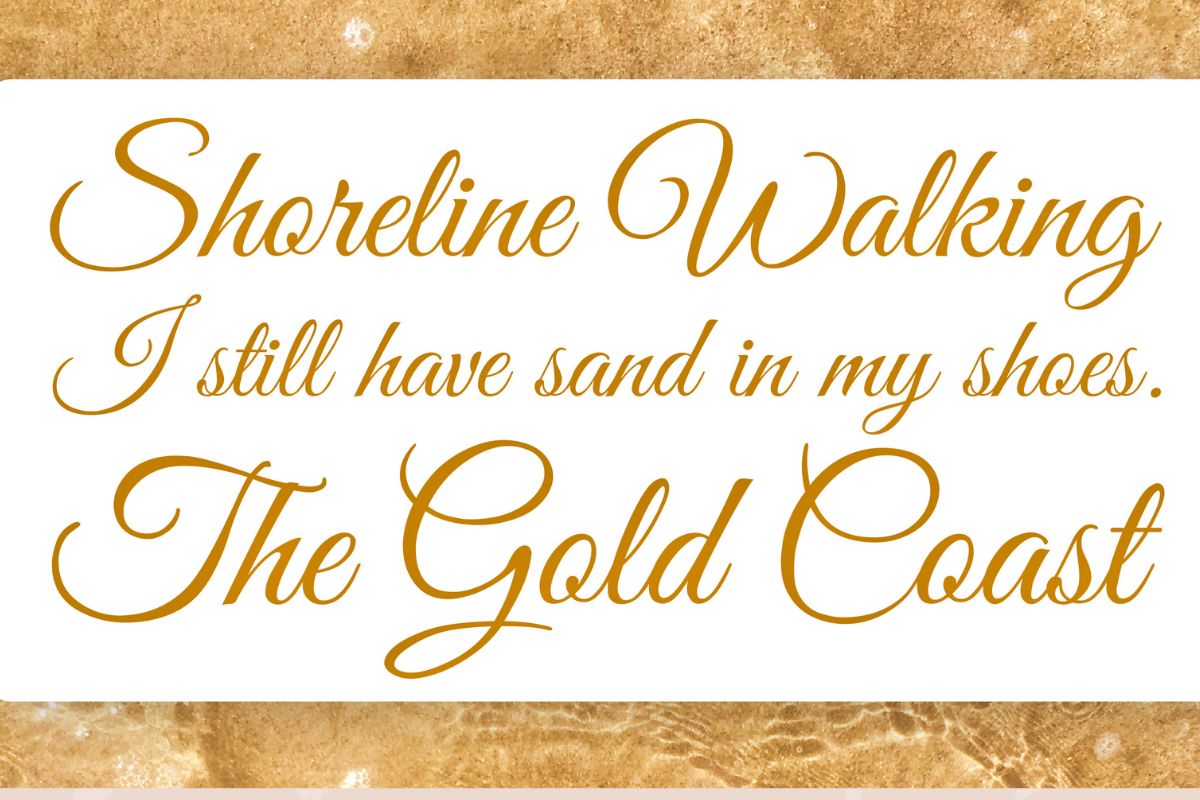
Amsterdam One – Phong cách hiện đại xen lẫn cổ điển
Font chữ này tạo điểm nhấn mạnh mẽ với những nét nối độc đáo, giúp các thiết kế bài đăng mạng xã hội trở nên chuyên nghiệp và bắt mắt hơn.
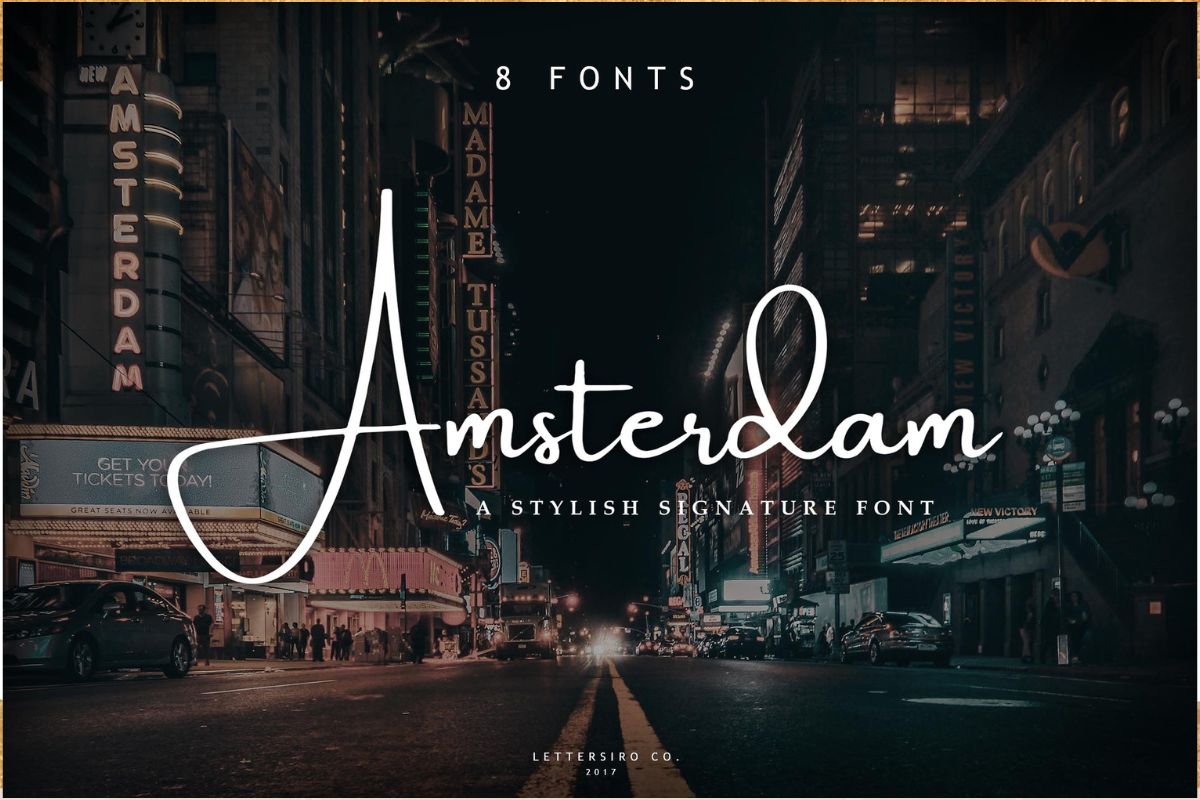
The Seasons – Font Serif sang trọng, đẳng cấp
Nếu bạn muốn thiết kế cho các nhãn hàng cao cấp hoặc sự kiện dạ tiệc 8/3, The Seasons với chân chữ sắc sảo sẽ mang lại vẻ ngoài cực kỳ sang chảnh.
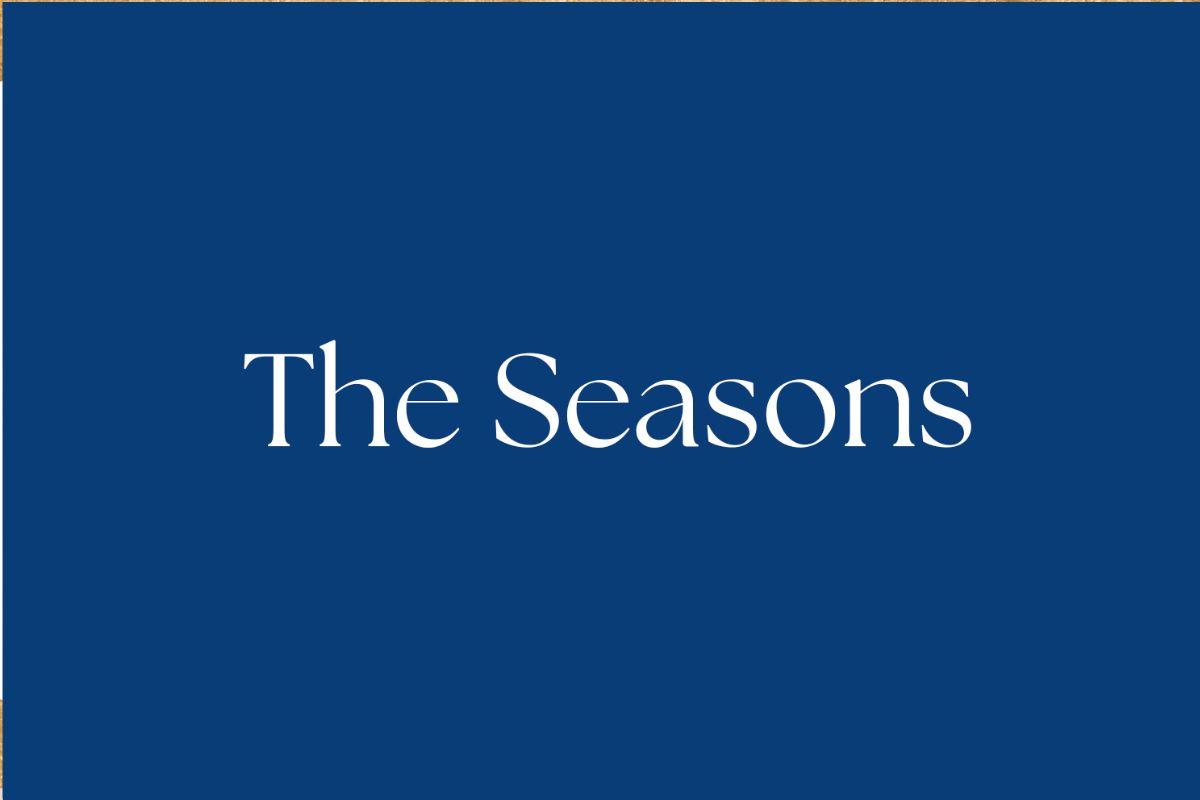
Merriweather – Sự kết hợp hoàn hảo giữa độ dày và tính thẩm mỹ
Một font chữ Serif dễ đọc, cân đối, giúp truyền tải những đoạn thông điệp dài một cách trang trọng.
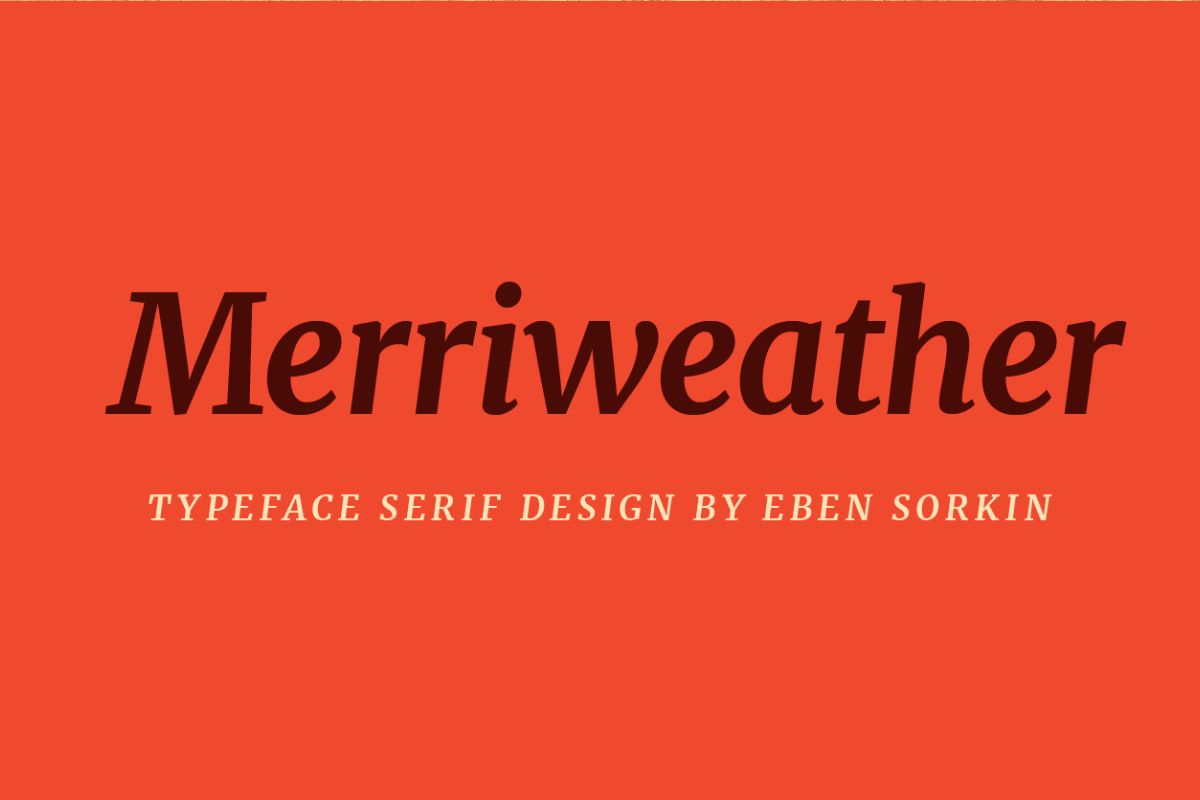
Tổng hợp font chữ 8/3 Việt hóa miễn phí 2026
Để tránh tình trạng lỗi dấu gây mất thẩm mỹ cho bản thiết kế, các bộ font Việt hóa luôn là lựa chọn ưu tiên hàng đầu. Dưới đây là 5 cái tên sáng giá nhất giúp lời chúc ngày Quốc tế Phụ nữ của bạn trở nên hoàn hảo:
SVN-The Carpenter Font
Đây là một dạng chữ viết tay cực kỳ đa năng với hệ thống các ký tự thay thế vô cùng phong phú. Font chữ này sở hữu những đường nét thanh mảnh nhưng chắc chắn, giúp bạn dễ dàng tùy biến tiêu đề thiệp 8/3 theo phong cách thủ công tinh tế.
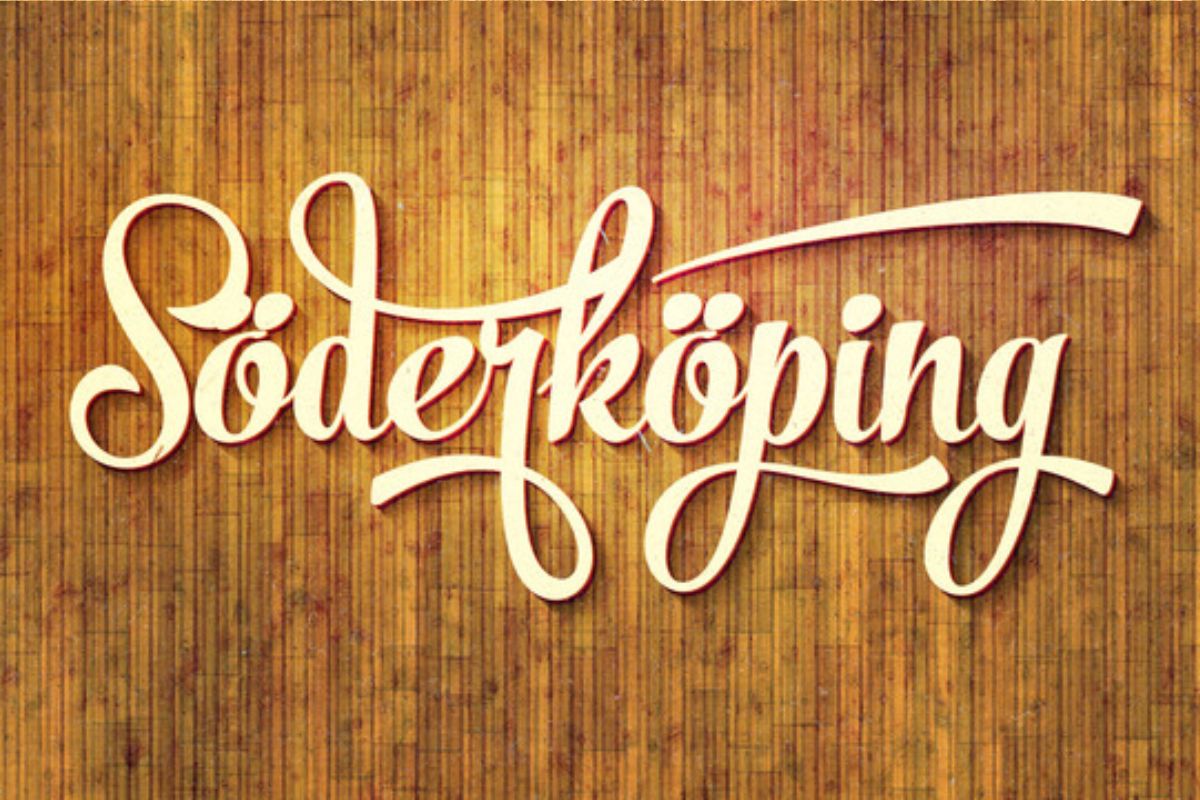
SVN-Silver Font
Nếu bạn đang theo đuổi phong cách tối giản nhưng sang trọng, SVN-Silver là lựa chọn không thể bỏ qua. Nét chữ mảnh khảnh, hiện đại của font này cực kỳ phù hợp để làm tiêu đề trên các poster sự kiện lớn hoặc banner trang trí tại các cửa hàng thời trang, mỹ phẩm.
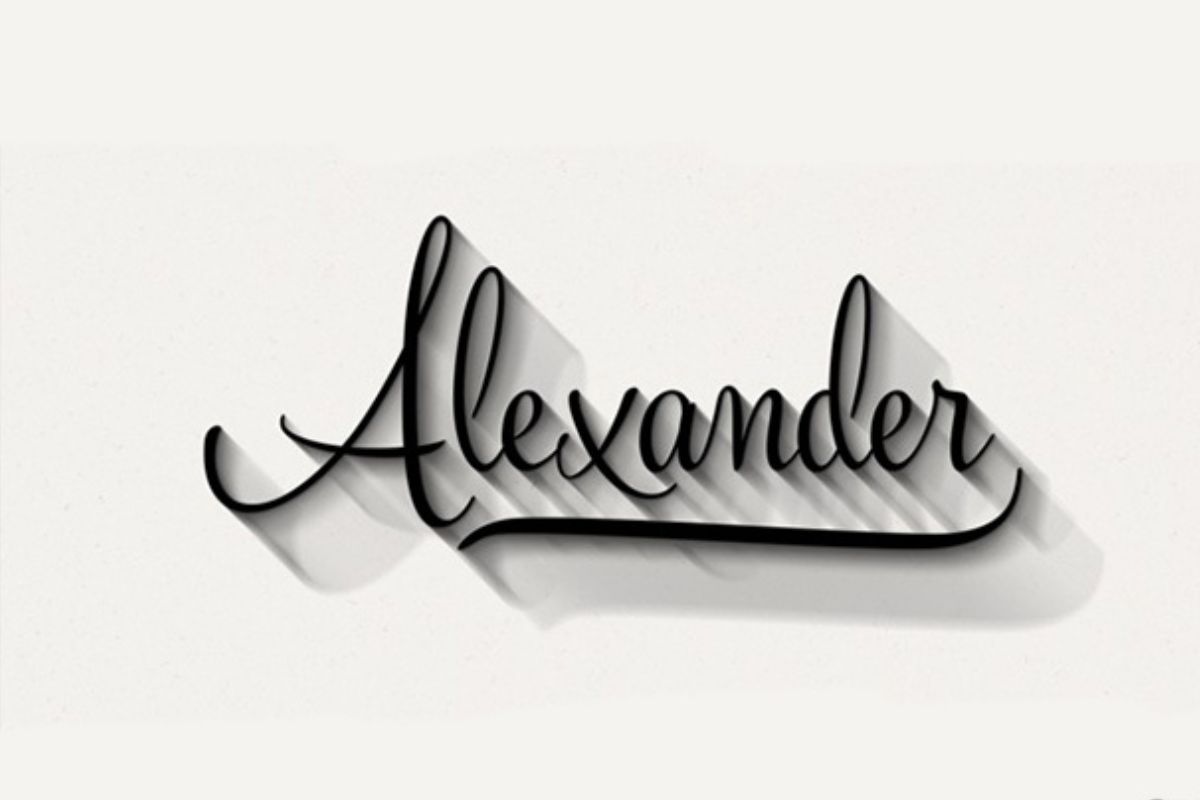
UVF Slim Tony Font
Slim Tony mang trong mình âm hưởng của phong cách retro thập niên cũ nhưng lại được tinh chỉnh để giữ được sự thời thượng cho năm 2026. Đây là vũ khí bí mật cho những thiết kế dành cho giới trẻ, tạo nên sự năng động và phá cách cho các bài đăng mạng xã hội.
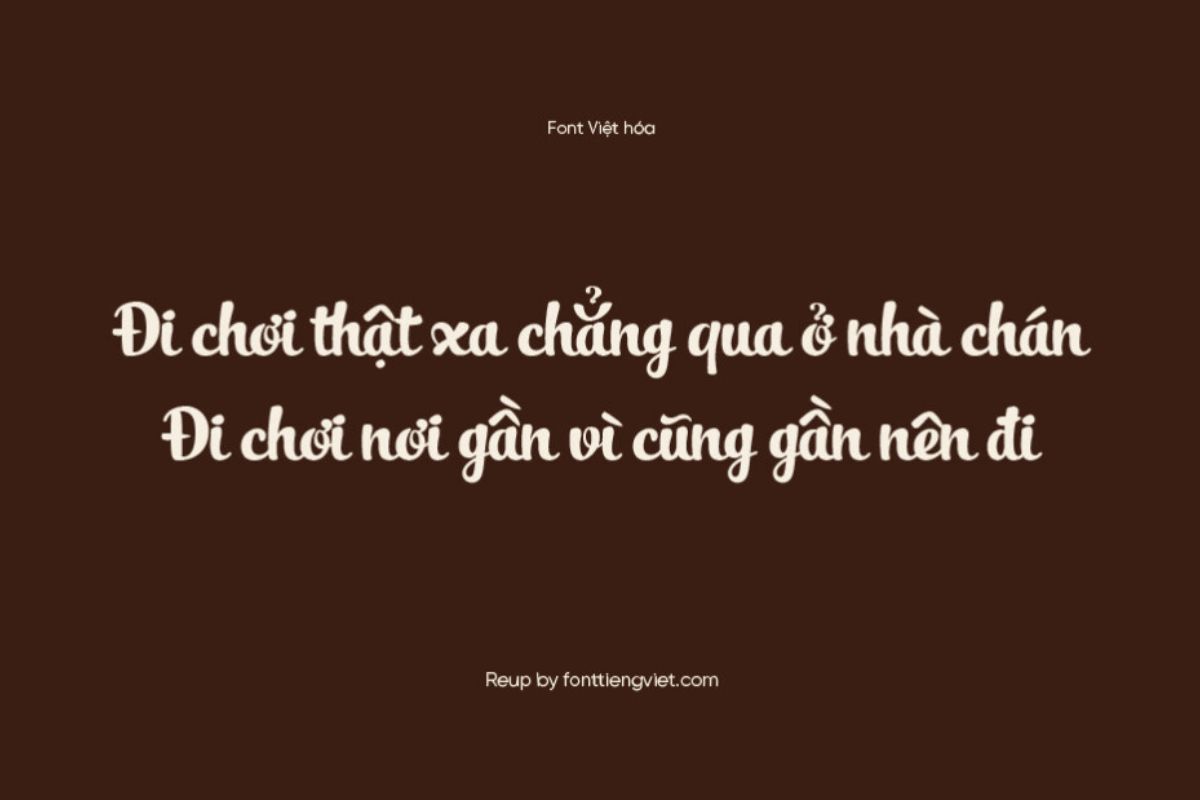
SVN-Amethyst Font
Sở hữu những đường uốn lượn đầy quyến rũ và nữ tính, SVN-Amethyst giống như một dải lụa mềm mại trên bản thiết kế. Font chữ này đặc biệt ăn ý với các chủ đề liên quan đến chăm sóc sắc đẹp, spa hoặc các sản phẩm cao cấp dành riêng cho phái đẹp.
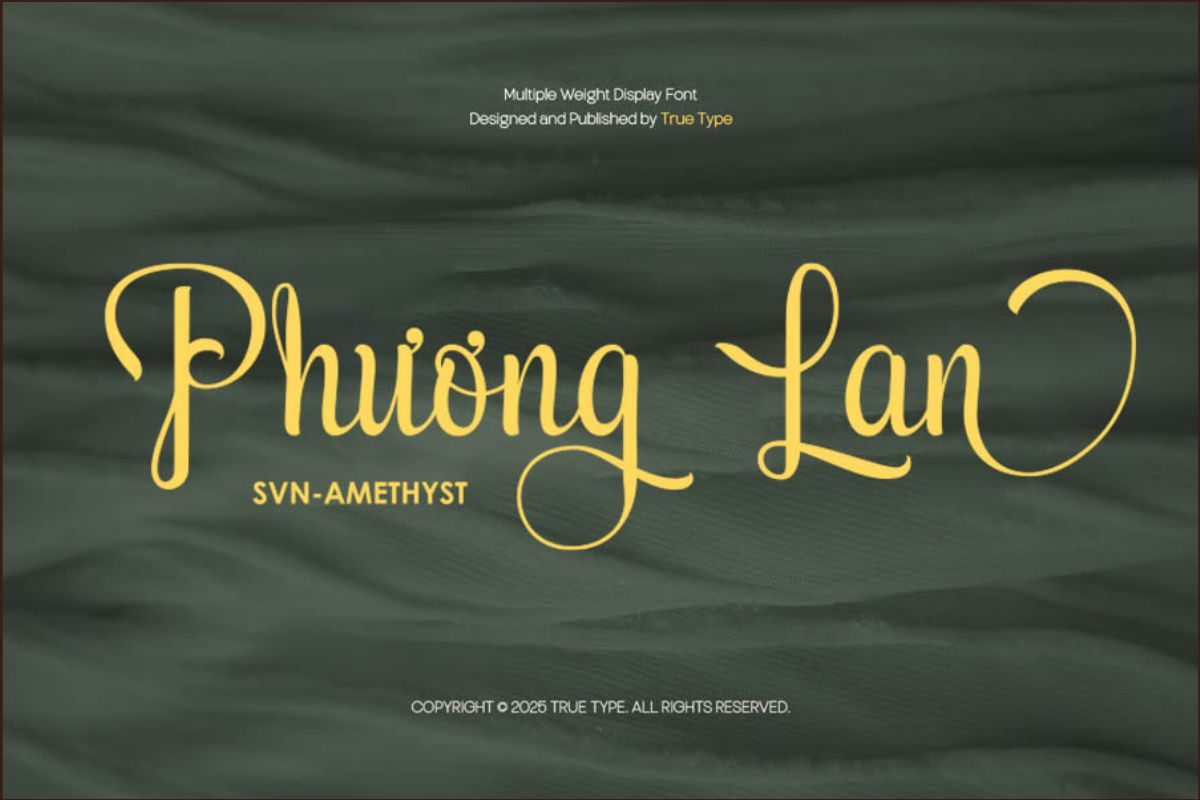
SVN Zara Elyse Font
Một font chữ script hiện đại, phóng khoáng và có tính ứng dụng cao, điểm mạnh của Zara Elyse là khả năng hiển thị rõ nét, không bị rối mắt, giúp bạn dễ dàng phối hợp với nhiều loại nền ảnh khác nhau, từ ảnh thiên nhiên rực rỡ đến các tông màu pastel dịu nhẹ.
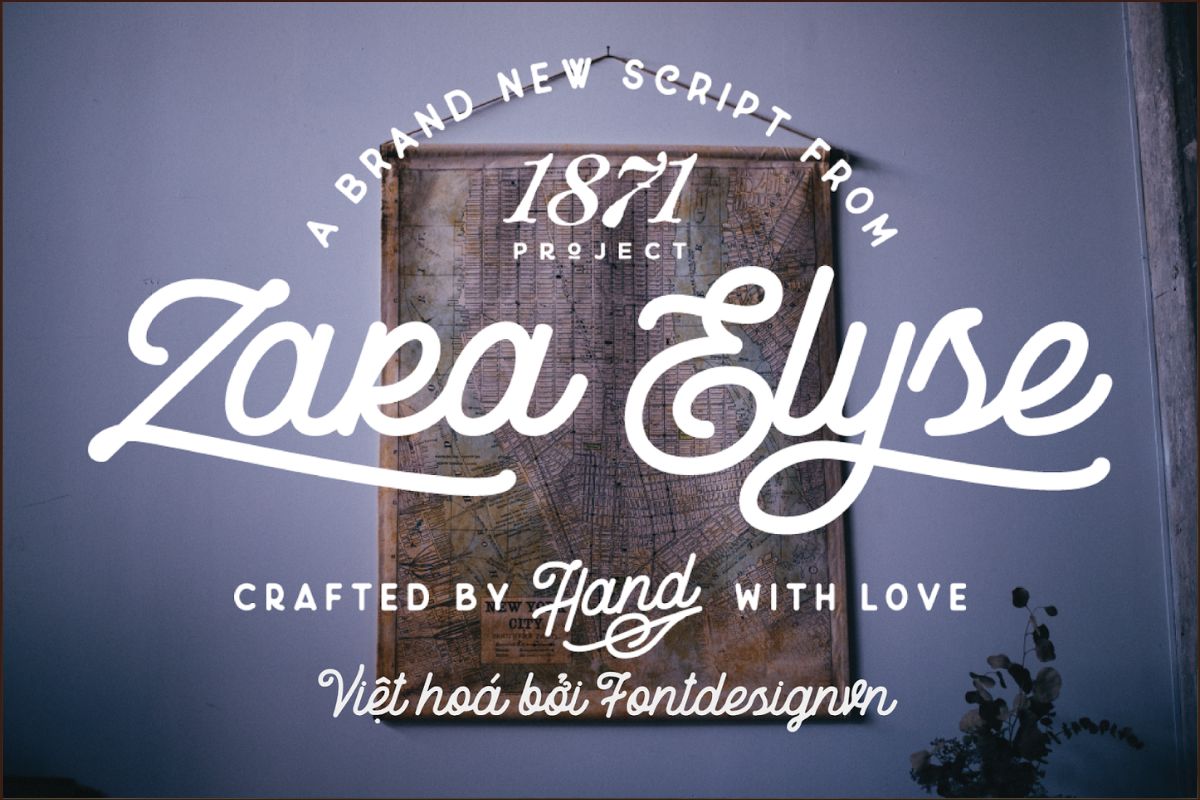
Các mẫu font chữ 8/3 viết tay nét thanh nét đậm ấn tượng
Kiểu chữ nét thanh nét đậm không đơn thuần là một lựa chọn thẩm mỹ, mà nó còn là biểu tượng gợi nhắc đến sự khéo léo, đảm đang và nét dịu dàng đặc trưng của người phụ nữ Việt Nam. Những đường nét uốn lượn uyển chuyển dưới đây sẽ giúp thiết kế của bạn trở nên có hồn hơn bao giờ hết:
Font VN Griffiths
VN Griffiths thường xuyên góp mặt trong các mẫu thiệp mời sự kiện trang trọng nhờ vào cấu trúc chữ vô cùng chuẩn mực. Font chữ này tái hiện lại phong cách thư pháp phương Tây cổ điển với những nét sổ đậm chắc chắn và nét hất thanh mảnh. Nếu bạn đang thiết kế một tấm thiệp tri ân dành tặng cho đối tác nữ hoặc cấp trên, đây chính là sự lựa chọn tinh tế nhất để thể hiện lòng tôn trọng.
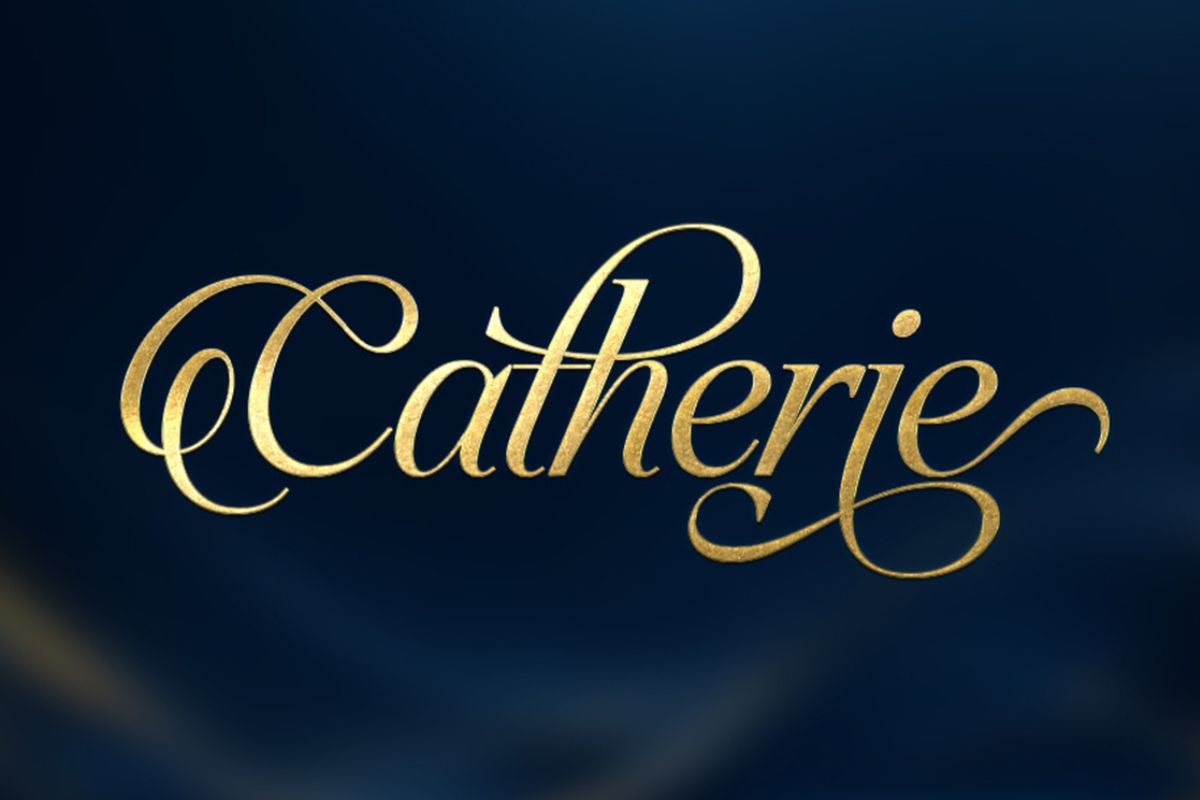
VN Lovelista
Đúng như tên gọi, VN Lovelista mang trong mình một hơi thở lãng mạn, ngọt ngào và đầy chất thơ. Với các nét nối giữa các chữ cái được thiết kế mềm mại như những dải lụa, font chữ này cực kỳ thích hợp để các đấng mày râu sử dụng khi thiết kế thiệp chúc mừng riêng tư dành tặng cho vợ hoặc bạn gái. Nó giúp lời chúc trở nên chân thành và ấm áp hơn.
Font VNI Zap
Nếu bạn lo ngại các font chữ viết tay quá rắc rối sẽ làm rối mắt người xem, thì VNI Zap chính là giải pháp cứu cánh. Font chữ này đi theo triết lý đơn giản nhưng không đơn điệu, tập trung vào việc tạo ra cảm giác thư thái, dễ chịu cho người đọc. Các nét chữ thanh thoát giúp bố cục thiết kế trở nên thông thoáng, rất phù hợp cho các bài đăng mạng xã hội nhân ngày 8/3.
Lựa chọn đúng font chữ 8/3 chính là cách bạn thể hiện sự trân trọng và tinh tế đối với những người phụ nữ tuyệt vời xung quanh mình. Hy vọng với danh sách 45+ mẫu font chữ Việt hóa cực đẹp và đa dạng phong cách trên đây, bạn sẽ sáng tạo nên những tác phẩm ấn tượng và ý nghĩa nhất.